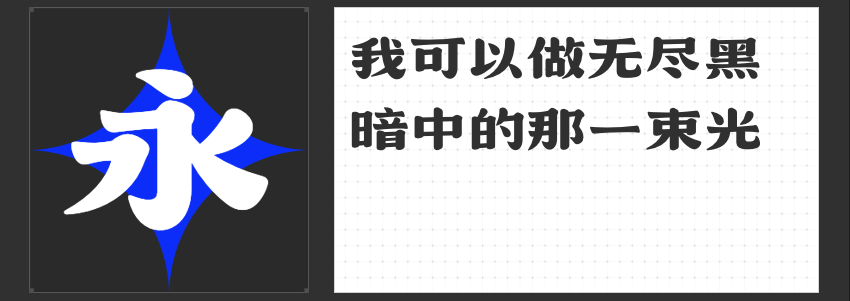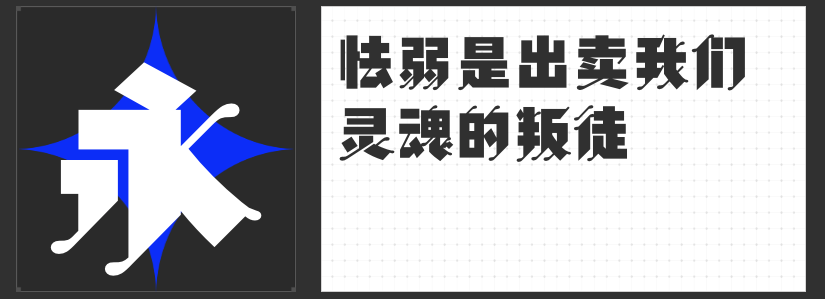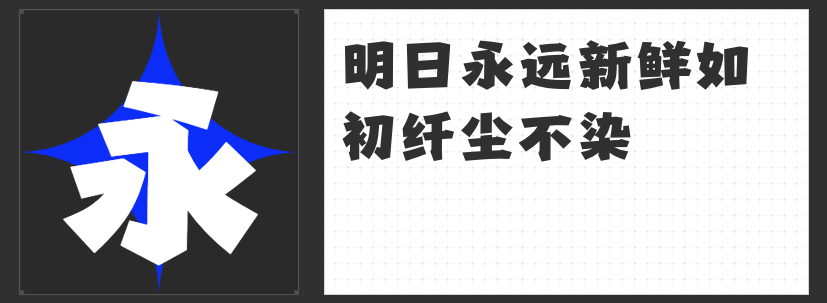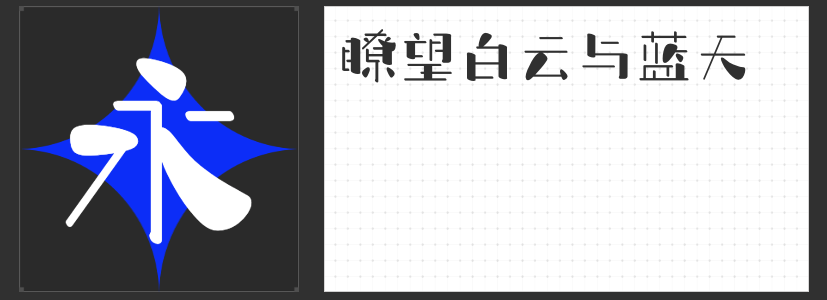
设计新锐必备:四款风格化字库字体解锁视觉创意新维度
在平面设计的多元表达中,字体不仅是信息载体,更是塑造氛围、传递情绪的核心元素。以下四款兼具艺术性与功能性的字库字体,以独特的造型语言为设计注入鲜活生命力,助你突破常规视觉框架。
一、字恋狂石头简
这款字体以反叛传统的姿态重构汉字形态,细笔画呈现棱角分明的几何切割,却在末端暗藏手写笔触的微妙弧度,形成理性与感性的视觉对冲。粗笔画的点缀如随机泼洒的墨点,与大量断笔处理的交接处共同营造出破碎重组的动态感。其错位偏移的结构布局打破汉字的静态平衡,尤其适合需要制造视觉冲突的先锋设计,在海报、品牌标识等领域能瞬间抓住观者视线。
二、高手字斋平行体
作为概念型设计字体,高手字斋平行体通过独特的笔画平行排列系统构建出立体悬浮的视觉幻象。每个字符的横竖笔画均保持等距间隔,形成类似建筑结构的网格秩序,却在关键转折处通过微妙的角度偏移打破机械感。这种虚实相生的处理方式,使其在科技主题包装、动态数字界面等场景中,能自然营造出数字时代的冷峻美学。
三、高手兵克楷黑体
在传统楷书框架中注入工业设计思维,这款字体通过横画末端上挑的锐利刀锋与转折切角的几何化处理,将书法的流动韵律转化为更具张力的视觉符号。加粗的字重赋予其作为标题的绝对存在感,而适度压缩的中宫结构则确保了小字号下的可读性,使其成为商业广告、文化展览等需要平衡艺术性与实用性的场景的理想选择。
四、 高手兵克柔书体
以圆润饱满的笔画勾勒汉字轮廓,高手兵克柔书体通过15%的横向压缩比例创造出独特的扁宽形态,既保留了手写书法的温润质感,又通过标准化处理确保了多字符排版的整齐度。其略带弹性的曲线转折暗合传统隶书神韵,却以更现代的视觉语言呈现,尤其适合文化创意、生活美学类项目的品牌视觉系统构建。
这四款字体通过差异化的造型策略,为设计师提供了从实验性探索到商业落地的多元解决方案。它们共同诠释了当代字体设计的核心趋势:在功能性与艺术性之间寻找精妙平衡,让每个字符都成为传递创意的视觉诗篇。